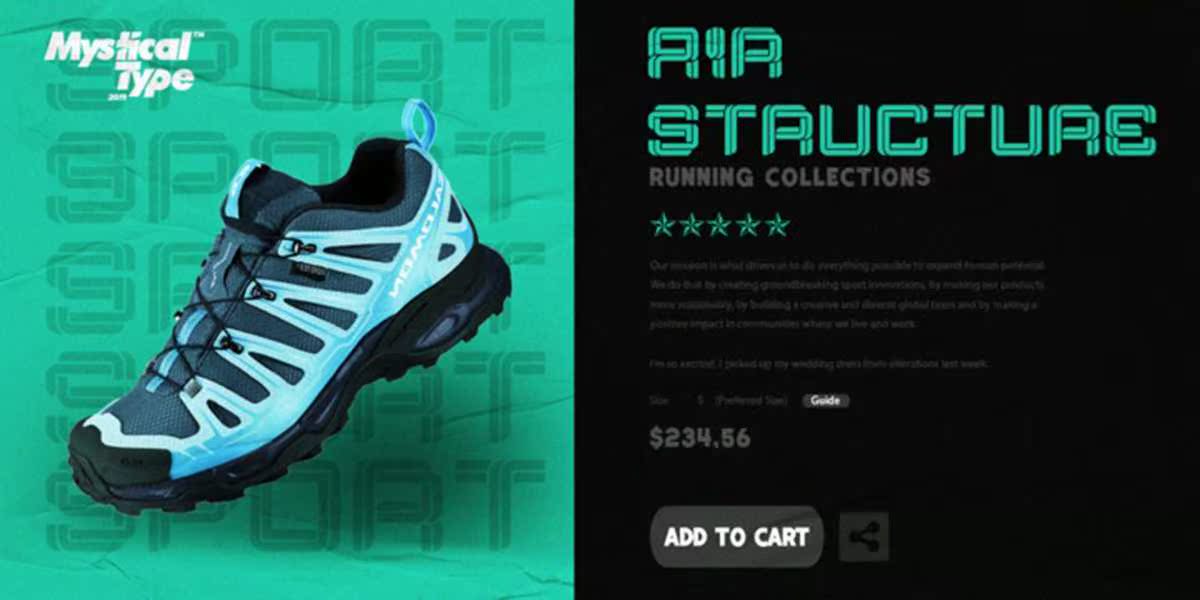
Athaarisabold,ModernSports,以戏剧性的动作和强烈的情感,为您的最新项目提供现代化的运动体验。它适用于品牌项目、标志、婚礼设计、社交媒体、广告、产品包装、产品设计、标签、摄影、水印、邀请函、文具和任何需要现代化运动风格的项目。Athaarisabold,通过戏剧性的行动和对你最新项目的强烈感受,现代体育运动需要现代体育运动。它适用于品牌项目、标志、婚礼设计、社交媒体、广告、产品包装、产品设计、标签、摄影、水印、邀请函、文具和任何需要现代体育运动风格的项目。